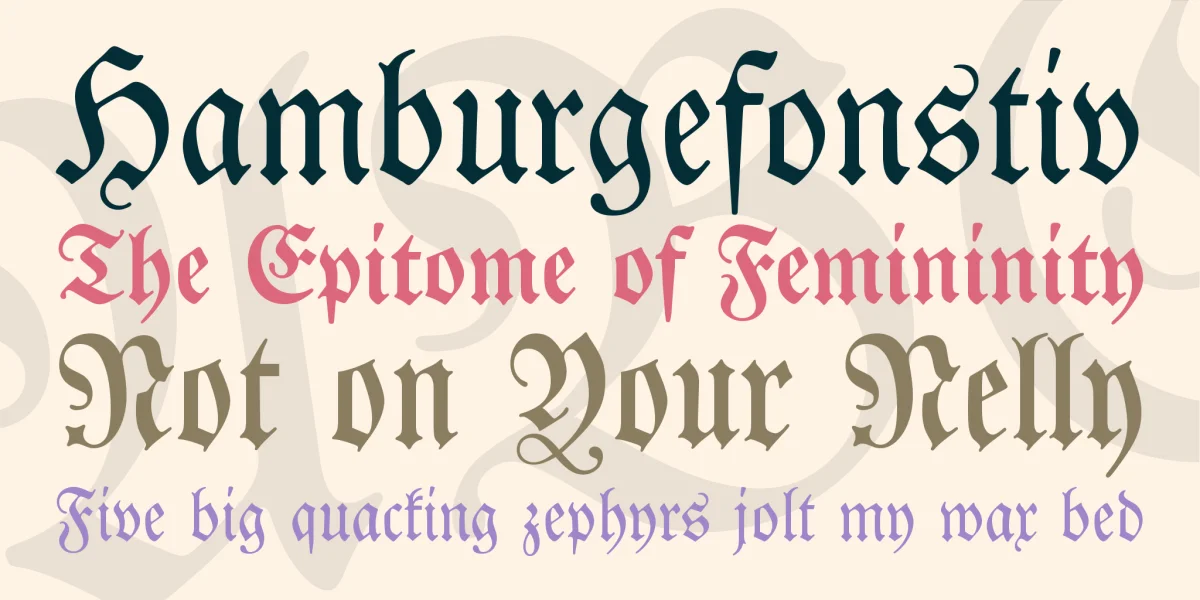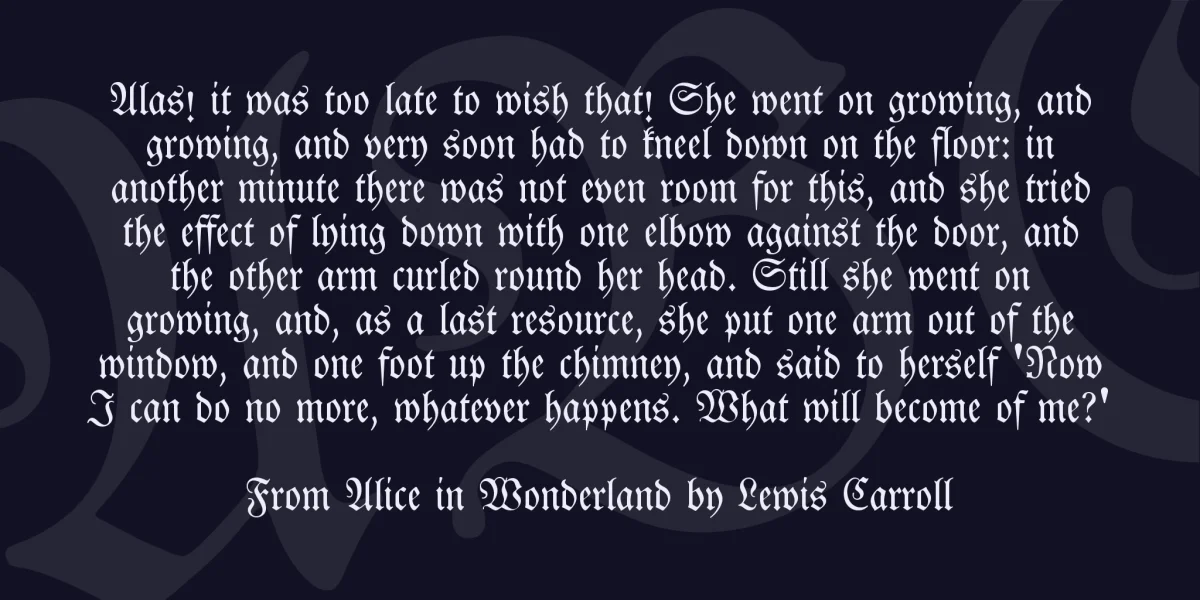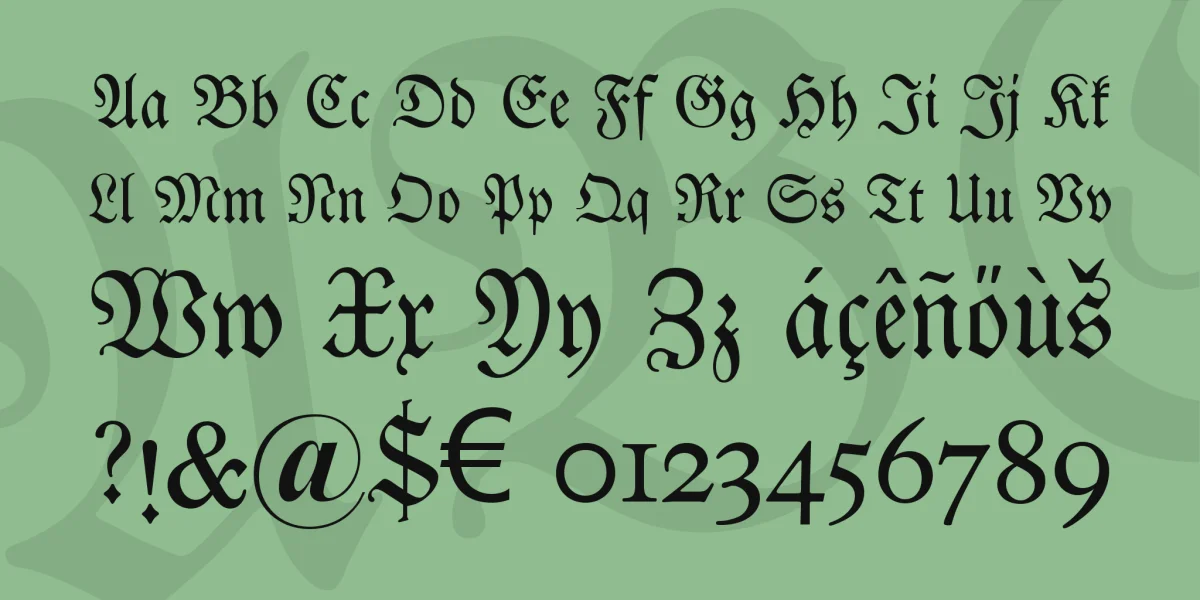
Die Lutherische Fraktur aus der berühmten Frankfurter Gießerei-Eigenolff-Luther nach einer Vorlage von 1708 ist die edelste der noch vorhandenen alten Frakturschriften.